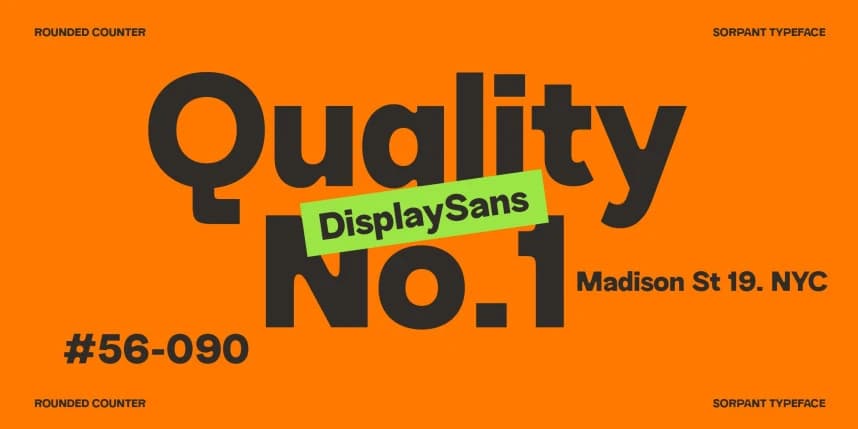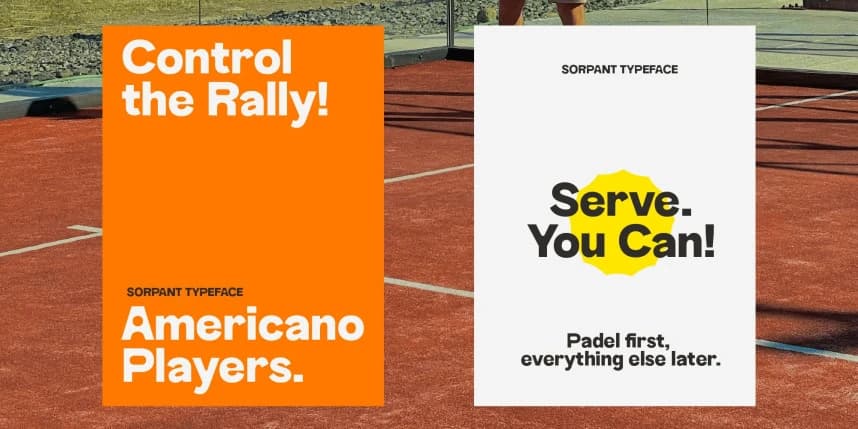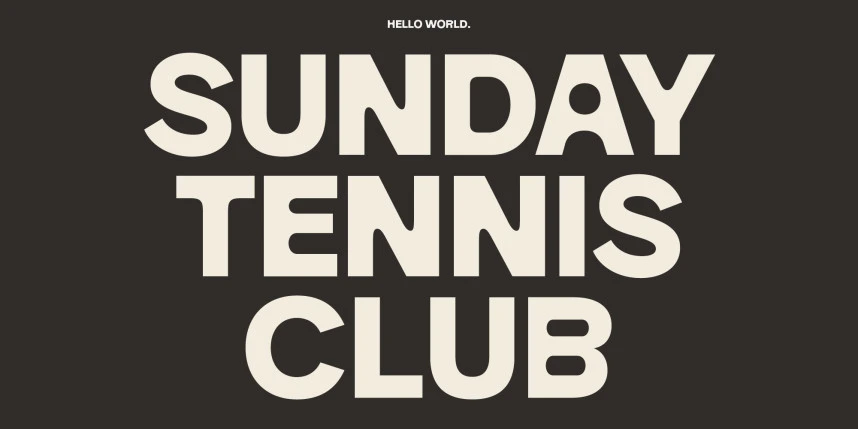
Sorpant Font
SORPANT Font, sadeliği kendine özgü bir dokunuşla yeniden tanımlayan modern bir gösterim yazı tipidir. Temiz bir sans serif temeline dayalı olan bu yazı tipi, benzersiz yuvarlatılmış iç boşluklarıyla öne çıkar; her harfe daha yumuşak ve daha yaklaşılabilir bir kişilik kazandırır ve cesur, kendinden
SORPANT Font, belirgin bir dokunuşla basitliği yeniden tanımlayan modern bir gösteri yazı tipidir. Temiz bir sans serif temeli üzerine kurulu olan bu yazı tipi, kendine özgü yuvarlatılmış iç boşluklarıyla öne çıkar ve her harfe daha yumuşak, daha ulaşılabilir bir kişilik kazandırır; bu da cesur ve kendinden emin varlığını kaybetmeden öne çıkmasını sağlar.